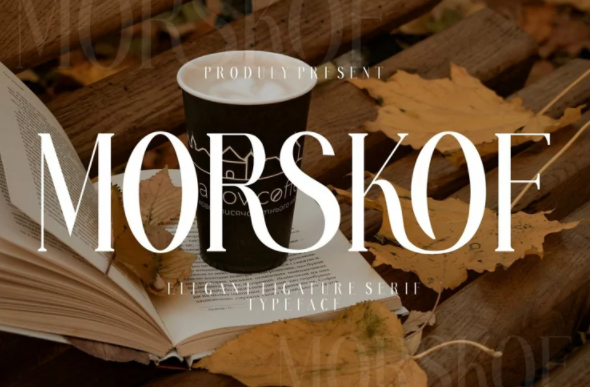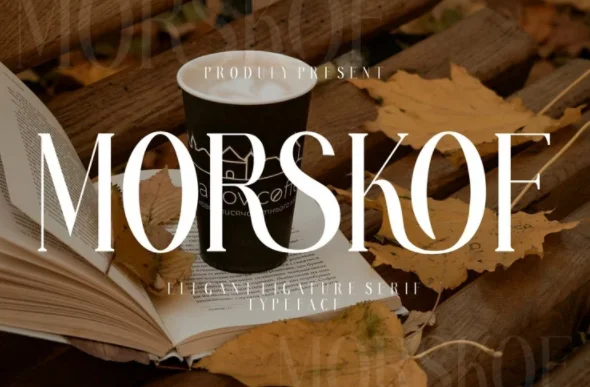
Название: Morskof Font (2022)
MORSKOF - элегантный и стильный шрифт с засечками - этот шрифт одновременно современный и ностальгический и отлично подходит для логотипов, журналов, социальных сетей. Они уже подобраны и готовы к использованию для вашего следующего дизайна! Для тех из вас, кто нуждается в элегантном, стильном, шикарном и современном дизайне, этот шрифт создан для вас!
MORSKOF создан с использованием возможностей OpenType и включает лигатуры, цифры, пунктуацию, а также поддерживает другие языки.